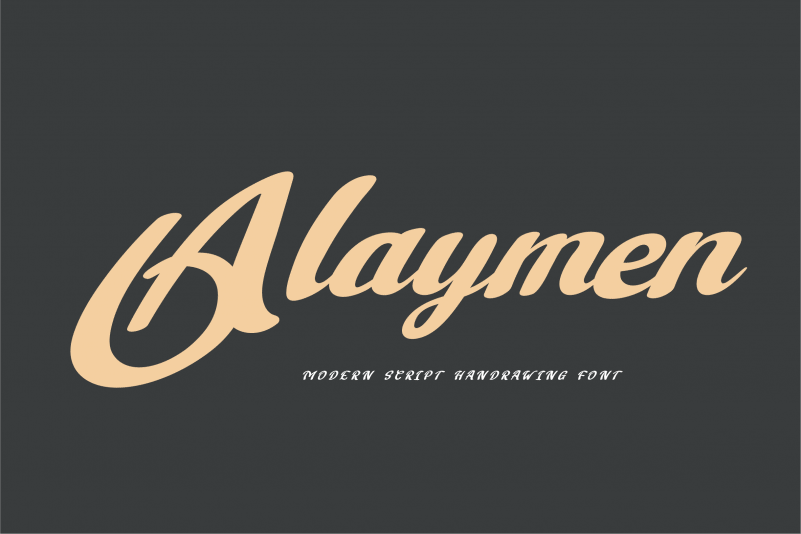
Alaymen Script Font – Download Grátis
A Alaymen Script Font é uma deliciosa mistura de elegância e fidelidade à arte da escrita chinesa. Desenvolvida por Twinletter, esta fonte cai na categoria de Fonts para Escrituras Rústicas, trazendo um estilo fluido e personalizado que se adaptará perfeitamente a qualquer projeto de design que você possa estar criando. Com sua forma curvilínea e rica em detalhes, a Alaymen Script é uma excelente escolha para designers apaixonados por arte chinesa ou escrita livre. Seu uso pessoal está disponível gratuitamente, mas incentivo um pouco mais de generosidade com uma doação via PayPal se você estiver satisfeito e quer apoiar o criador. Você pode fazer sua doação através deste link: [https://paypal.me/abahrozi](https://paypal.me/abahrozi). A Alaymen Script é perfeita para trabalhos que exijam um toque delicado, seja em logos, identidades corporativas ou até mesmo em criações de arte digital. Sua simplicidade e complexidade são equilibradas de uma maneira que a torna uma fonte versátil que pode se adaptar às mais diversas necessidades do seu design.